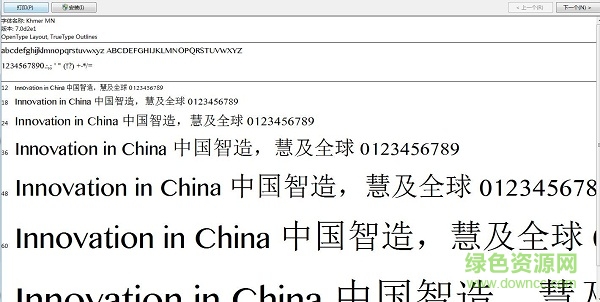
khmer mn 字體是Murasu公司為為蘋果ios系統(tǒng)設(shè)計(jì)的一款柬埔寨高棉語(yǔ)襯線字體,線條舒展,清晰度高,字形飽滿優(yōu)美,適用范圍廣泛,有需要者歡迎免費(fèi)下載!
1.高棉語(yǔ)又稱柬埔寨語(yǔ),是柬埔寨的官方語(yǔ)言,屬于南亞語(yǔ)系;
2.高棉語(yǔ)使用者世界上約1700萬,分布國(guó)家有柬埔寨, 越南, 泰國(guó), 美國(guó)等;
3.高棉語(yǔ)的語(yǔ)音較為復(fù)雜,共有33個(gè)輔音、27個(gè)元音符號(hào)和12個(gè)獨(dú)立元音。